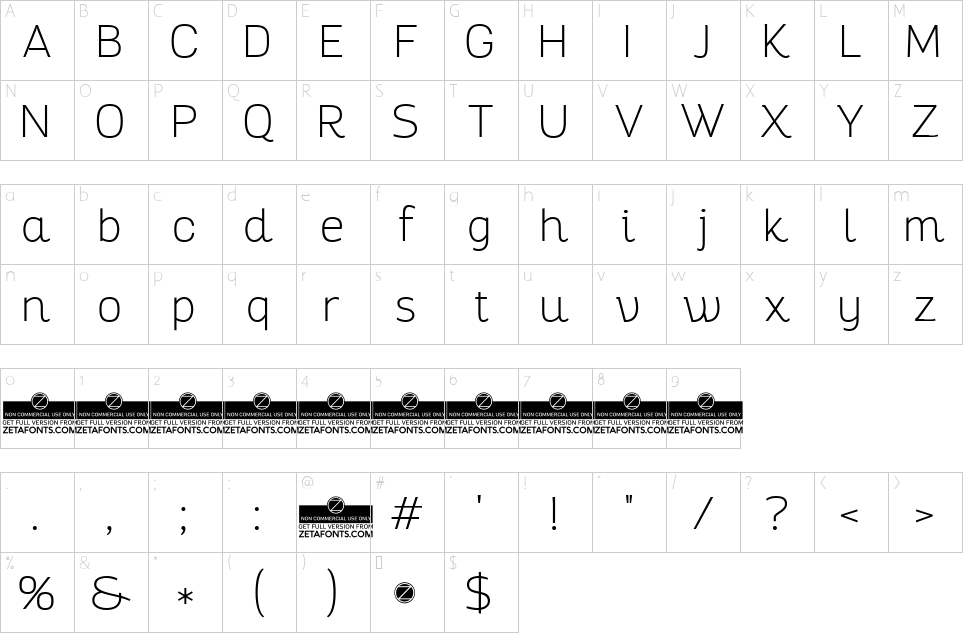
Altair Font – Fonte Grátis
Altair Font
A fonte Altair, desenhada pela Zetafonts, está agora disponível para download gratuitamente tanto para Windows quanto para Mac. Esta elegante fonte é perfeita para adicionar um toque especial a qualquer projeto gráfico, seja para criar belos efeitos de texto ou para personalizar layouts de websites. Com seus traços finos e elegantes, Altair permite que você personalize a aparência de seu design de maneira única. Com mais de 11 mil downloads, a Altair já ganhou o respeito e o reconhecimento de designers profissionais e aspirantes. Experimente já e explore todas as possibilidades que esta fonte tem a oferecer.
Mapa de caracteres da fonte Altair Font